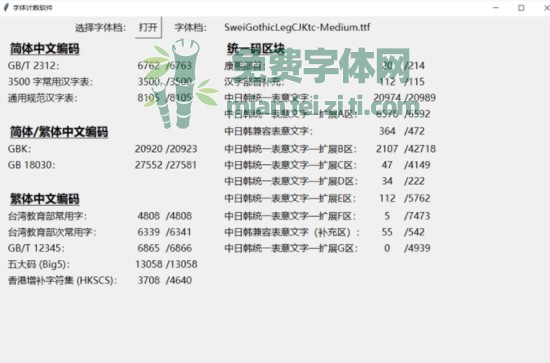
狮尾腿圆体:又一款把思源黑体改造成圆体字形免费商用字体资讯
狮尾腿圆体是台湾的大神Max又一款基于思源黑体变圆改造,和狮尾圆体的差别在有长腿,更加简明现代化的字体。支持简体中文、繁体中文、韩文与日文;欢迎大家自由应用、自由优化、自由改作!
狮尾腿圆体和狮尾圆体差别在有没有拔脚。狮尾圆体是“有拔脚”的,字会较圆,但是会造成有些字因直接去掉腿后左右不平衡、左右不对衬的“悬空”问题。使用“腿”系列就比较不会有失衡的问题,但是看上去还是会有黑体的感觉。
字数统计
狮尾腿圆体是基于思源黑体改造而成,所以无论是简体还是繁体基本上都不缺字,并且拥有7个字重。